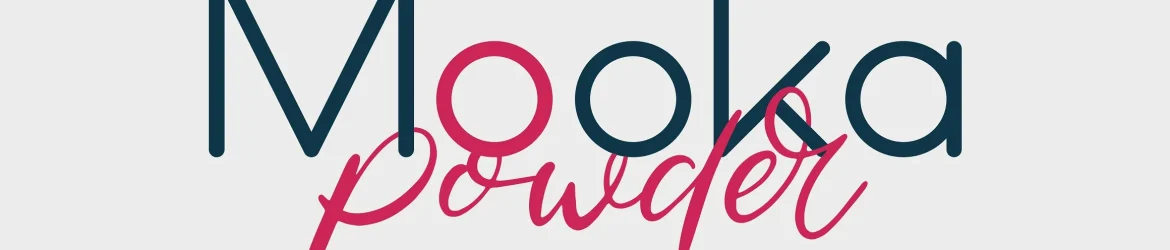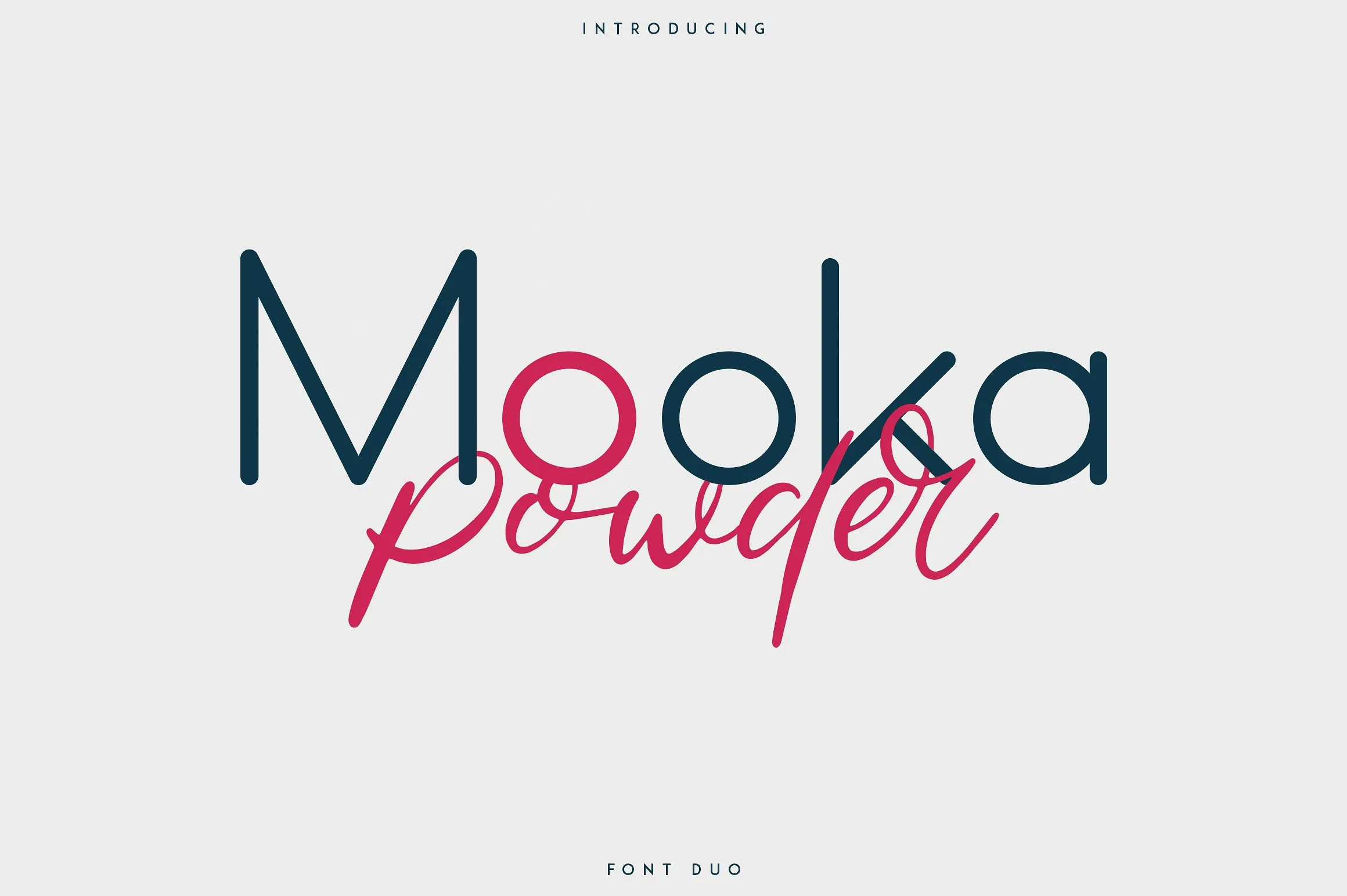
Mooka Powder Font Duo – Fonte Grátis
Mooka Powder Font Duo
Descubra a Mooka Powder Font Duo, uma elegante combinação de duas fontes: uma serifada e outra script, criada por VPcreativeshop. Especificamente, esta é uma dupla moderna e clara de fontes sem serifas com um total de sete estilos de fonte, ligaturas e suporte multilíngue. A Mooka Powder Font Duo é perfeita para trabalhos em grandes e pequenos tamanhos, tornando-a uma opção versátil e funcional que será essencial para qualquer designer gráfico. Perfecto para criar designs dinâmicos e atraentes sem comprometer o estilo elegante da fonte script.